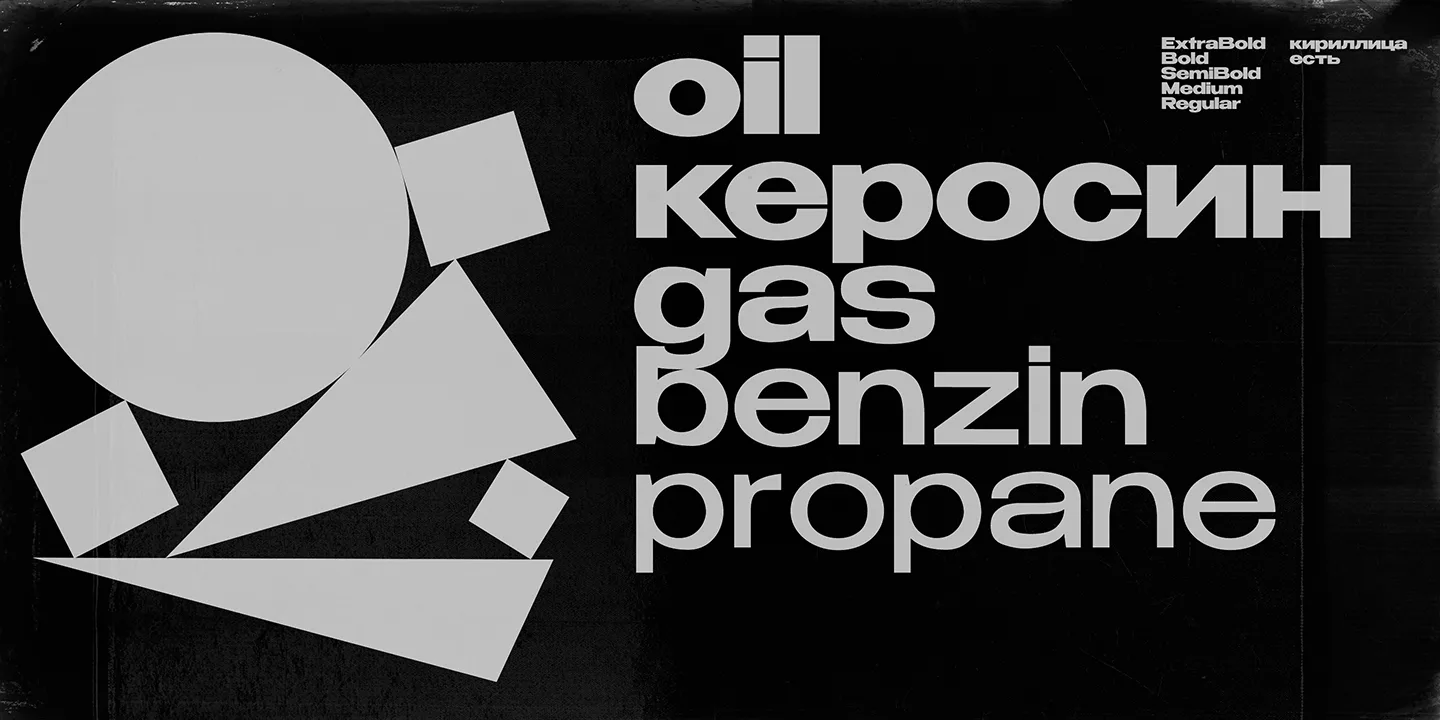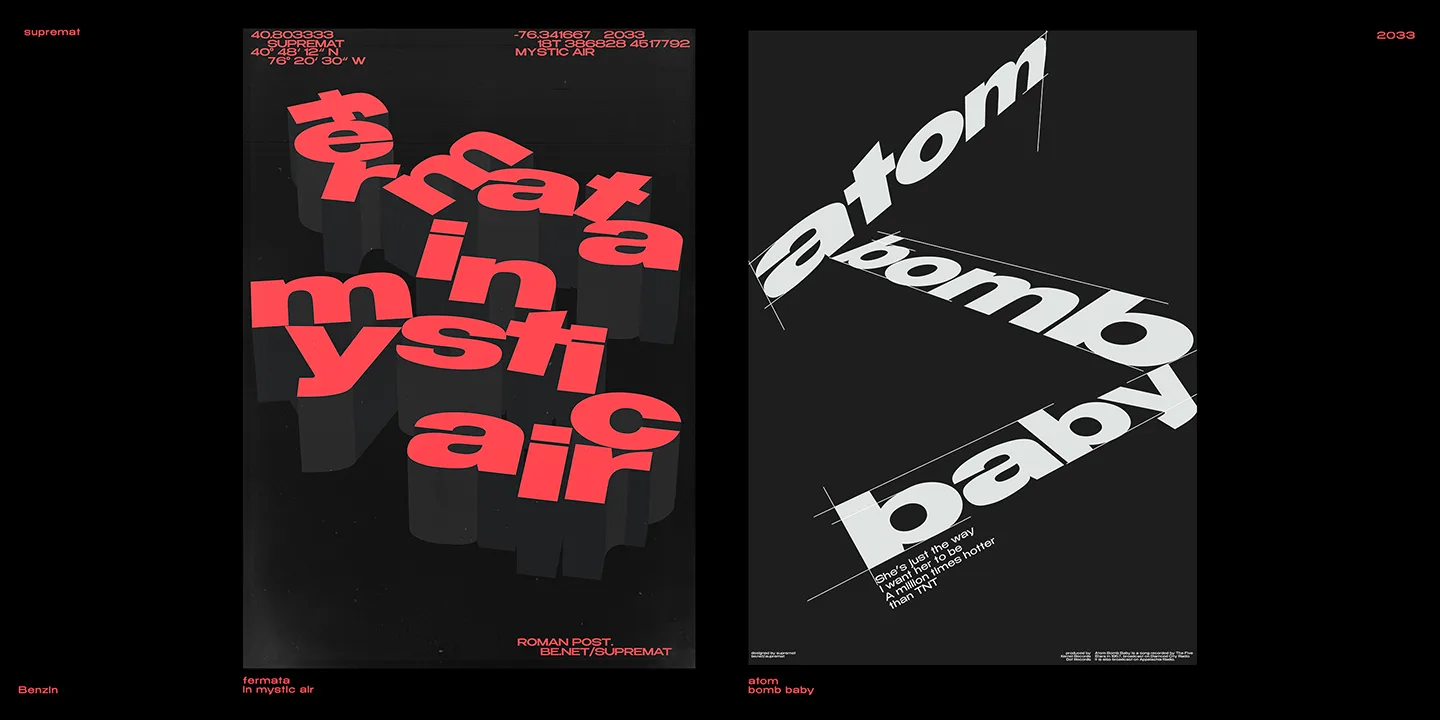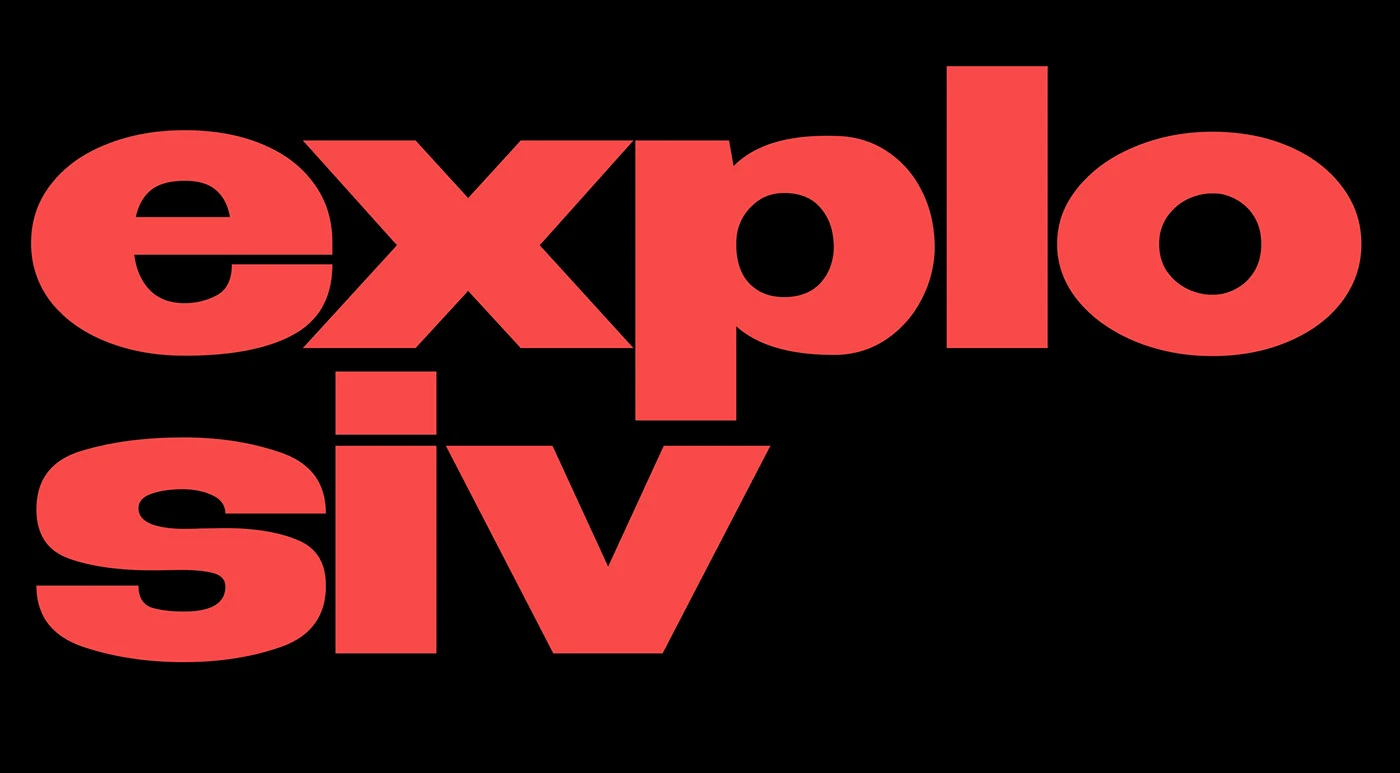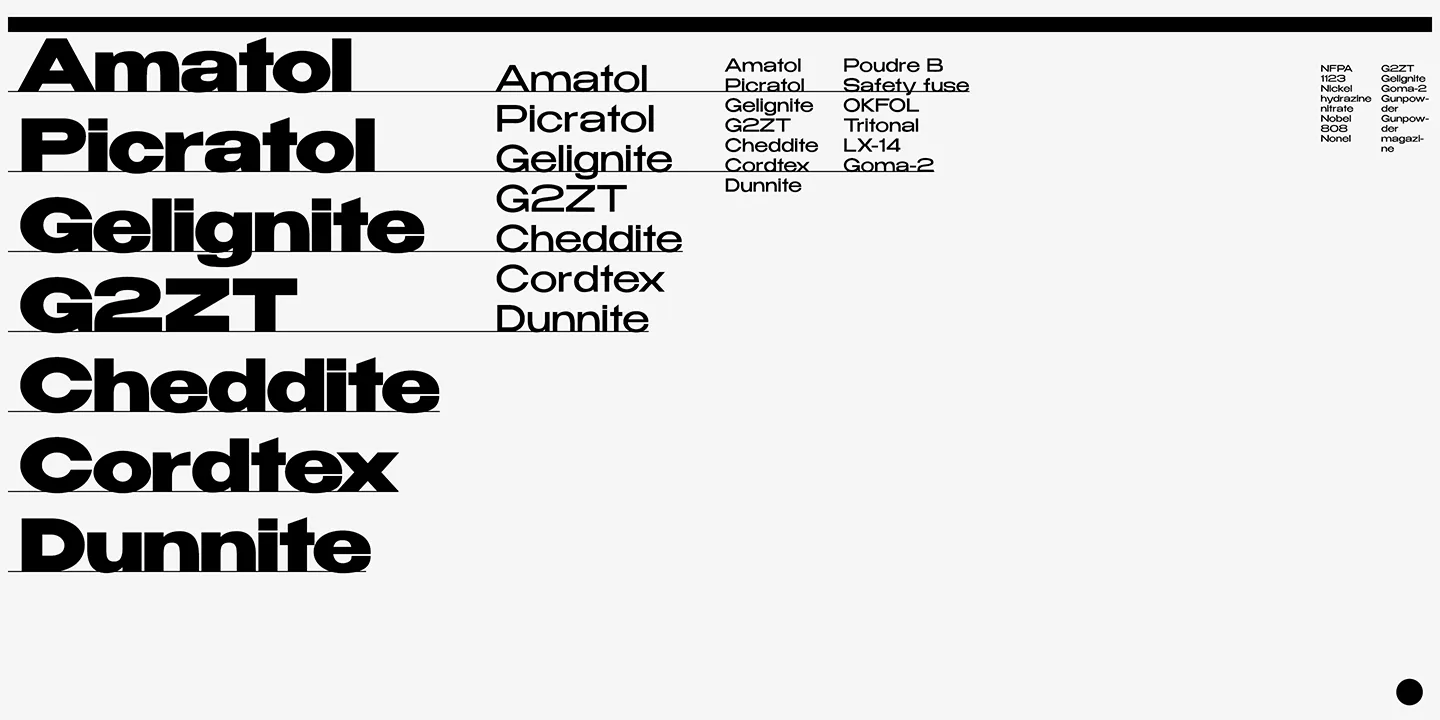
Font Benzin Việt hóa là bộ phông chữ không chân (Sans-serif) mang phong cách công nghiệp mạnh mẽ, lấy cảm hứng từ thiết kế cơ khí, động lực học và các bảng hiệu trạm nhiên liệu thập niên trước. Với cấu trúc chữ hình học vững chãi, các đường nét dứt khoát cùng trọng tâm thị giác cực lớn, phông chữ này là lựa chọn hàng đầu cho các thiết kế logo phụ tùng ô tô, bao bì thiết bị điện tử, đồ uống năng lượng và các ấn phẩm mang phong cách Industrial cá tính. Doozypack.vn cung cấp link tải Font Benzin Việt hóa chuẩn kỹ thuật, giúp bạn sở hữu trọn bộ phông chữ cá tính này mà không lo gặp bất kỳ lỗi hiển thị dấu thanh nào khi thiết kế in ấn.
Đặc điểm thẩm mỹ độc đáo của bộ font Benzin
Benzin không đi theo sự thanh mảnh nhẹ nhàng; nó tạo ra một ngôn ngữ thị giác đầy uy lực, gợi nhắc đến thế giới của máy móc, động cơ và sức mạnh cơ khí.
Phong cách Industrial Sans-serif mạnh mẽ và vững chãi
Đặc trưng lớn nhất của Font Benzin Việt hóa là các con chữ được xây dựng với độ dày nét (weight) cực lớn và cấu trúc mở rộng theo chiều ngang. Thân chữ thẳng đứng kiêu hãnh kết hợp cùng các góc vát sắc sảo tạo nên một khối văn bản vô cùng kiên cố. Khi đặt phông chữ này làm tiêu đề trên bao bì, thương hiệu của bạn sẽ ngay lập tức toát lên vẻ nam tính, bền bỉ và khẳng định chất lượng kỹ thuật hàng đầu.
Cấu trúc hình khối lấy cảm hứng từ cơ khí và động lực học
Các ký tự của Benzin Font Family sở hữu tỷ lệ chuẩn mực, các đường giao nét vuông vức mang lại cảm giác kỷ luật và chính xác tuyệt đối. Sự kết hợp này giúp tiêu đề bản thiết kế giữ được sự đĩnh đạc, hiện đại và không hề gây cảm giác nặng nề, rất phù hợp với các mẫu hộp giấy định vị ở phân khúc kỹ thuật và thể thao.
Ưu điểm nổi bật của bản Font Benzin Việt hóa
Khi ứng dụng các phông chữ công nghiệp vào thị trường trong nước, sự chỉn chu về dấu câu là yếu tố quyết định đến tính chuyên nghiệp của ấn phẩm:
- Khắc phục triệt để lỗi dấu tiếng Việt: Phiên bản Việt hóa đã được đội ngũ thiết kế trau chuốt thủ công từng dấu câu. Các dấu sắc, huyền, hỏi, ngã, nặng được vẽ với độ dày đồng điệu cùng thân chữ gốc, không gây cảm giác chắp vá hay làm biến dạng cấu trúc hình học.
- Kiểm soát hiện tượng tràn mực (Dot Gain) tại khe chữ nhỏ: Các khoảng hở bên trong chữ cái của Benzin (như chữ ‘e’, ‘a’) khá hẹp. Khi in trên giấy có độ thấm mực cao như giấy Kraft, mực có thể bị lan làm bít kín các lỗ hở này. Bạn nên giữ size chữ tiêu đề tối thiểu từ 10pt trở lên để bảo đảm độ sắc nét.